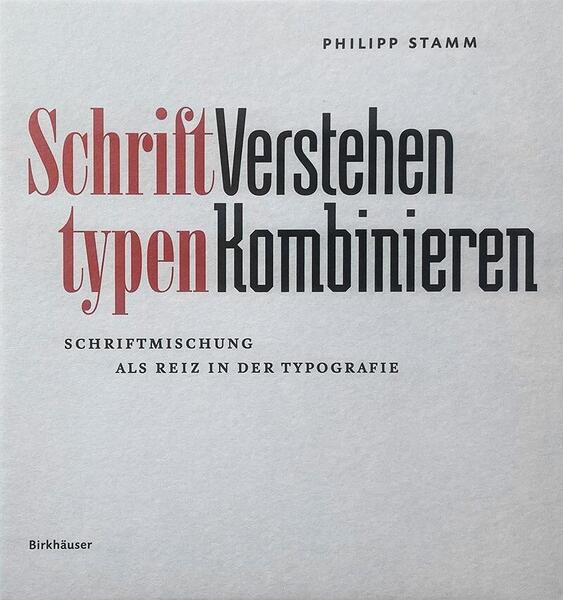
Im Schweizer Birkhäuser Verlag ist ein umfangreiches Buch zum Thema Schriftmischung erschienen. Der Autor Philipp Stamm ist gelernter Schriftsetzer und Professor für Schriftgestaltung, Typografie, Corporate Design an der Fachhochschule Nordwestschweiz.
Aus dem Klappentext: »Dieses Handbuch zeigt, dass sich für das Mischen von Schriften Kriterien bestimmen lassen. Es vermittelt durch das detaillierte Betrachten der Schriftgestalt und eine erneuerte Schriftklassifikation ein vertieftes Verständnis für die Vielfalt an Schriftformen und erarbeitet durch die systematische Analyse von Analogie und Kontrast die dringend benötigten Erkenntnisse zum Kombinieren von Schriften. Ein unverzichtbares Standardwerk für Typografen und Grafikdesigner.«
Bevor das 360-seitige Buch die Kriterien der Schriftmischung tatsächlich angeht, stehen ganze fünf Kapital Einführung mit Grundlagen und Begriffserklärungen.
- »Historische Betrachtungen« mit einem Abriss zum Schrifteinsatz mit besonderem Hinblick auf Schriftmischungen
- »Grundformen | Maßsyteme« mit Begriffserklärungen wie Geviert, Laufweite, Schriftgröße usw.
- Satzschriftklassifikationen einschließlich eines eigenen Systems
- und »Schriftkonzepte«, d.h. Erklärungen zu Schriftfamilien bzw. digitalen Ausprägungen wie Variable Fonts
Die restlichen drei Kapital gehen dann die Schriftmischung direkt und ausführlich an. In Kapital sechs werden auf knapp 50 Seiten die möglichen Kriterien der Schriftgestaltung bis ins kleinste Detail hin ausgelotet. Dies ist in dieser Ausprägung wohl einzigartig. Strichstärke, Kontrast, Schriftlage, Duktus, Kehlung, Effekte, Füllungen, Farbe und so weiter. Vierzehn Gestaltmerkmale (zuzüglich Untergruppen) werden hier behandelt.
In Kapitel sieben folgt dann eine konkrete und praxisnahe Anleitung zur Anwendung der vorgenannten Kriterien bei der Schriftwahl. Den Abschluss des Buches bilden über 100 Seiten mit Schriftmischungs-Beispielen.
Fazit: Nach Jahren des Rezensieren von Typografie-Büchern freue mich über jedes Buch, das tatsächliche eine eigene Nische besetzt und nicht nur die fachübliche Lehre neu verpackt. Das vorliegende geht mit dem Thema Schriftmischung ein eigenes Thema an und tut dies auch auf eine ungemein detailreiche Weise. Das Werk gibt sich dabei in jeder Hinsicht als schnörkelloses, echtes Fachbuch. Text und Gestaltung versuchen gar nicht erst, Laien und Quereinsteiger mit bunten Bildern und möglichst einfachen Texten abzuholen. Das Buch eignet sich für Fachleute und jene, die es werden wollen.
Untertitel: Schriftmischung als Reiz der Typografie